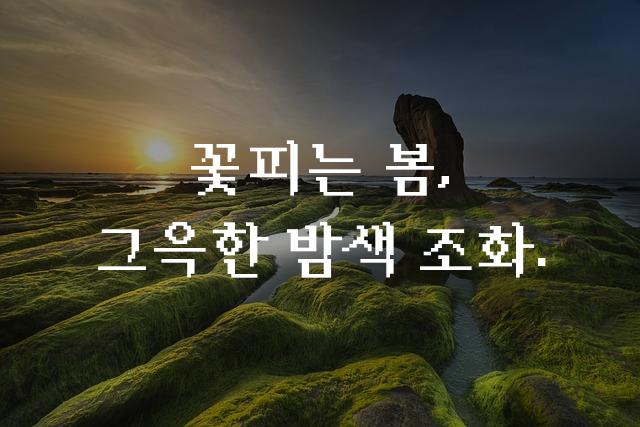
HBIOS-SYS는 이민서가 제작한 한국어 폰트로, 레트로한 감성과 픽셀 도트 스타일이 특징입니다. 고전적인 비디오 게임의 향수를 불러일으키며, 디지털과 아날로그의 경계에서 새로운 창의성을 제공합니다.
HBIOS-SYS은(는)
픽셀/코딩, 레트로, 감성적인, 복고풍, 게임 느낌 계열의 생김새를 가지고 있으며
웹/앱 디자인, 보고서/문서, 출판물 제목 등에서 자주 활용되며, 효과적인 메시지 전달에 적합합니다.
이 폰트는 기술/IT, 금융/비즈니스, 환경/에너지 분야에 잘 어울리며,
현대적, 전문적인, 단순한 느낌을 담고 있는 것이 특징입니다.